如何製作自己的字體模板
已發表: 2023-02-12如果您在這裡,您可能已經在互聯網上搜索了幾個小時以尋找完美的字體,但您沒有找到。 隨著創意品牌故事的門檻越來越高,您承受著讓您的設計看起來*恰到好處*的巨大壓力。 現在,您的攻擊計劃是創建您自己的字體,這個想法多棒啊!
創建字體並不像聽起來那麼難,而且在自定義字體的外觀和感覺時,這個過程可以打開機會的閘門。 當您製作自己的字體模板時,您可以控制線寬、襯線、密度等等。
有幾種不同的方法可以解決這個問題,根據您想要的風格,有多種方法可以創建數字解決方案以及手繪字體。 現在,我們將專注於動手方法並學習如何將您的作品變成現實生活中的字體。 以下是我們將介紹的內容:
選擇您要使用的字體或模板站點
如果你谷歌“製作你自己的字體”,你會發現足夠多的網站能夠讓你的藝術作品栩栩如生。 總的來說,他們大多遵循相同的系統,所以不要過分強調這一點。 為了幫助您對所有內容進行分類,我們推薦以下三個字體構建站點:
對於本教程,我使用 Calligraphr 來啟動我的項目。 這個平台是免費的,而且對初學者字體設計師來說超級友好。
收集你的材料
要開始使用自己的筆跡構建字體,您需要做一些事情。 至少,像樣的筆和紙是一個很好的起點。 要使您的創作過程更加活躍,請拿起尺子、量角器和您的計算機來查找創作靈感。 這將有助於您的繪圖一致性,尤其是當您向自定義字體添加大量花哨的內容時!
讓您的創造力盡情發揮。 如果您想製作完美的曲線和線條,那就去做吧。 想抓住您 3 歲的孩子,看看他們想出什麼嗎? 也利用它們。 這是製作您自己的字體的最佳部分——您可以確定它的外觀以適合您客戶的創意簡報。
無論樣式如何,您都希望在字體模板紙上使用深色筆作為最終產品。 確保您的線寬不會太細或太重——找中等粗細的東西。 我們使用了 Sharpie,因此您可以在最終項目中看到結果如何(劇透警告:字體看起來很粗)。
我們建議從鉛筆開始。 請記住,您始終可以勾畫草圖,然後用鋼筆進行細化。 在你完成之前擦掉任何塗鴉!
是時候練習你的字體了
根據您的字體繪製的自然程度,您可能需要也可能不需要在嘗試最終版本之前進行練習。
在您將在下一步下載的模板表上,您必須將多個字符放在一張紙上。 這意味著如果您弄亂了一個字母並且無法修復它,您可能需要重做一整張字符。 如果您的字體真的很複雜,那將非常耗費您的時間和耐心。
即使只有一次,也要練習你的字體,希望你能在最終版本中避免路上的顛簸。
現在就做吧
準備就緒後,從您選擇的站點下載並打印字體構建模板頁面。 這可能看起來像幾張紙,每個字母都有一個指定區域。 就像你練習過的那樣,只要畫出你想要的字體就可以了。
由於模板上的插圖將是您自己的字體,因此您希望它是正確的。 慢慢來,仔細檢查你的角色,給自己足夠的時間來做這件事,不要倉促行事。 您最不想看到的是在將字體安裝到計算機上並嘗試將其用於項目後發現字體中的錯誤。
是時候上傳和創建您的字體了
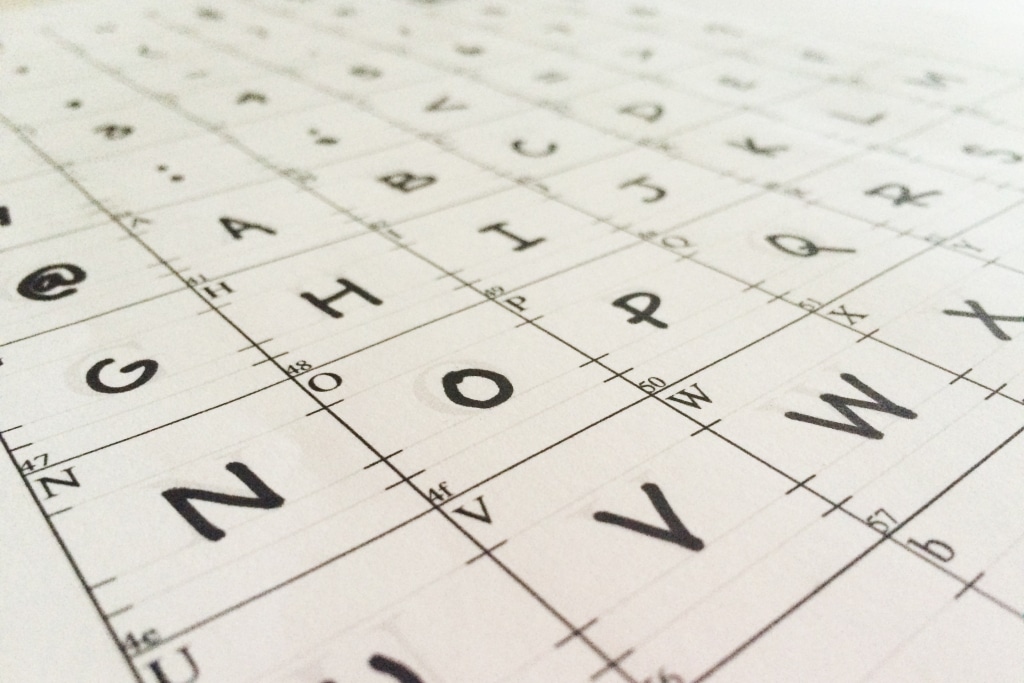
一旦您對自己的工作感到滿意,就可以將模板上傳到您決定使用的任何網站。 掃描您的字體模板,然後確保查看有關如何上傳它們的具體要求。
只需按照網站的說明進行操作,然後等待創建您的字體。 使用 Caligraphr,我們的等待時間大約為 7 秒,所以這是一個非常快的轉變。
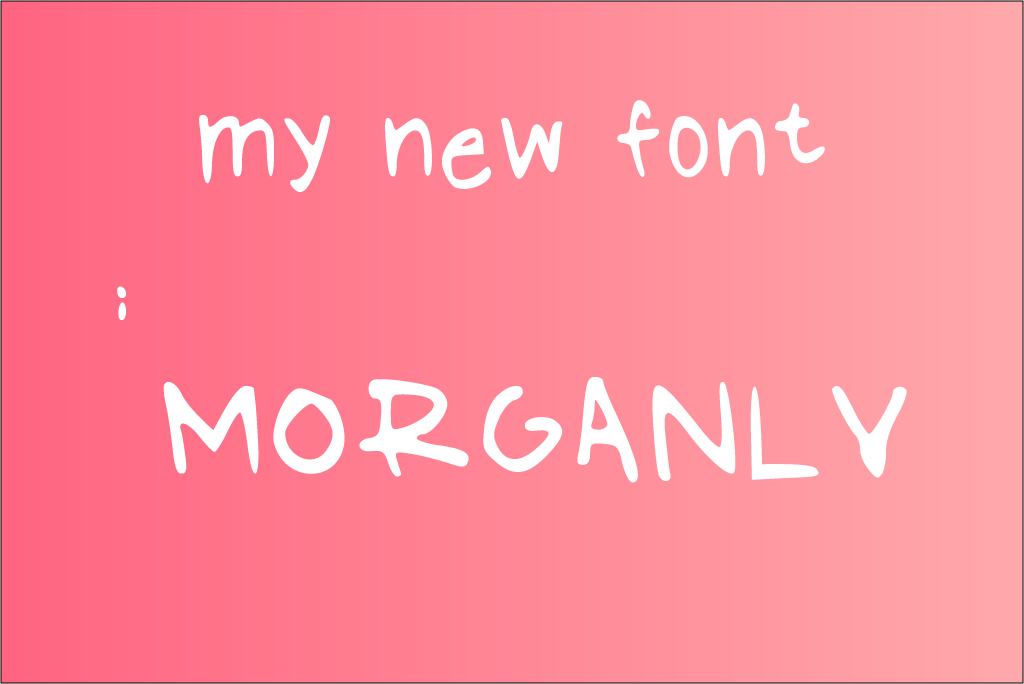
從繪製自定義字體中學到的一些東西:
- 看到兩行文字之間的那兩個點了嗎? 我們不知道這些是從哪裡來的,但它們與“M”字符相關。 因此,在上傳之前要格外小心,擦除模板上的任何額外標記。
- 使用模板編寫自己的字體會感覺很彆扭。 回想一下您第一次學習如何通過描寫字母寫字時的幼兒園; 創建自己的字體是一種類似的體驗。 考慮打印一些額外的模板表,這樣您就可以先練習掌握它。
- Sharpie 在紙上看起來不錯,但作為數字字體,線寬看起來要粗得多。 此外,字母的結尾沒有很好地複制,導致您在上面看到的字體看起來相當幼稚。
- 儘管這很困難,因為您要分別設計每個字母,但請盡量記住所有字符之間的關係。 出於某種原因,我們的小寫字母“t”最終比其他字母小得多(也高得多),所以它看起來有點格格不入。
老實說,您的第一種字體可能需要嘗試幾次。 雖然這是一個簡單的過程,但您可能會在每次製作自己的字體時學到新的更好的方法。
結論
隨著對獨特品牌故事的需求將我們的創意天花板推得越來越高,自定義字體和字體一直在增加。 希望這個字體構建教程能減輕您的挫敗感,因為您現在有能力將您的自定義字體創意變為現實!